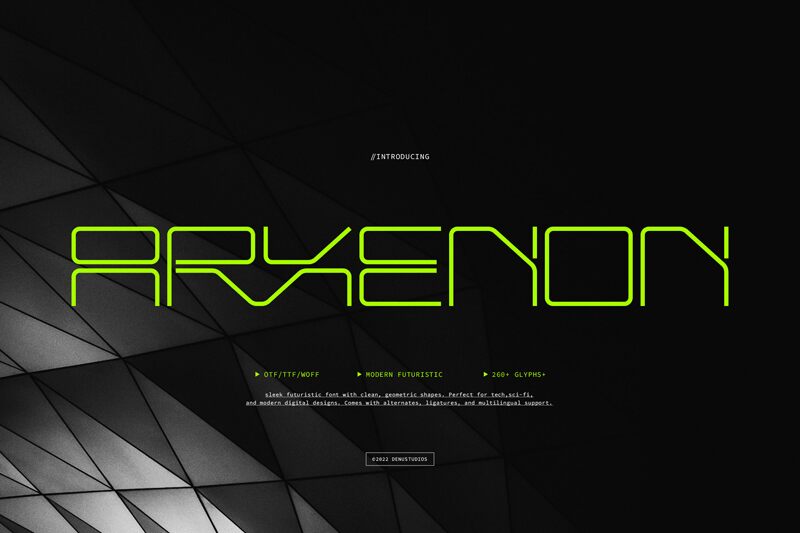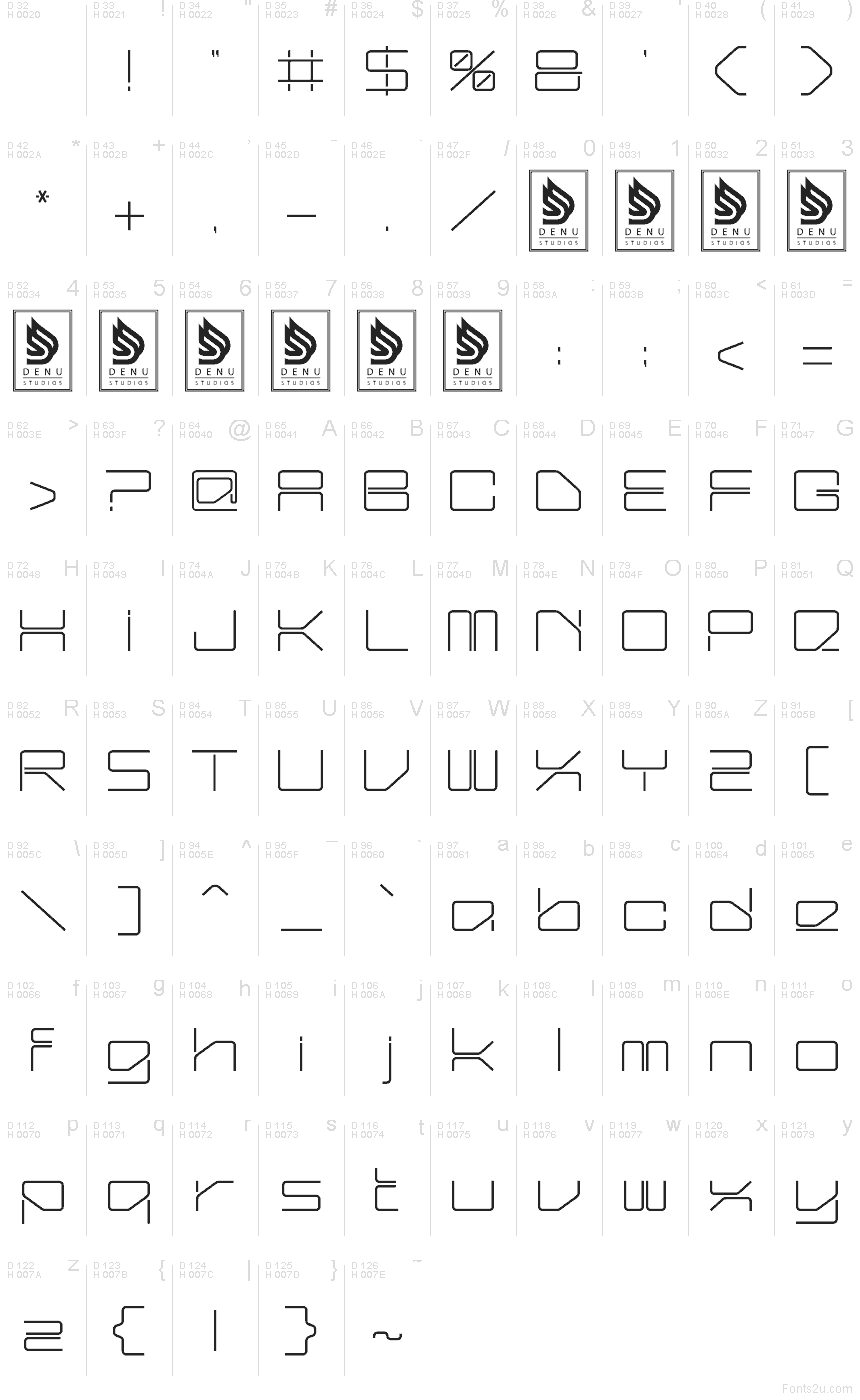
Arxenon od Denustudios to futurystyczny, bezpłatny krój typu display o płynnym, modułowym rytmie. Litery wyglądają, jakby zostały zbudowane z zaokrąglonych prostokątów o ściętych rogach, dzięki czemu całość balansuje gdzieś pomiędzy interfejsem science-fiction a elegancką plakietką w stylu retro-tech, z długimi poziomymi liniami, które zapewniają spokój zamiast chaosu.
Sprawia to, że ten darmowy font świetnie sprawdzi się w logo gier, plakatach wydarzeń technologicznych, okładkach muzycznych, tytułach czy brandingu, który potrzebuje syntetycznego sznytu, ale bez przesadnego cyberpunkowego klimatu. Sprawdza się najlepiej tam, gdzie formy mogą pozostać krótkie i widoczne – szerokie krzywe i kanciaste cięcia nadają nawet kilku literom odpowiednią prezencję, by stanowić podstawę logo lub kompaktowego nagłówka.